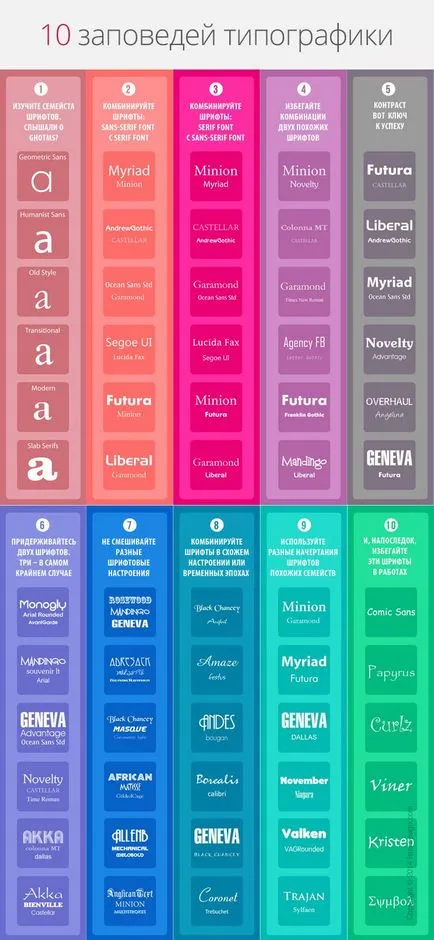
Как да изберем правилния шрифт за логото пълната информация logowiks
Повечето дизайнери са съгласни, че изборът на шрифта - това е един от най-важните неща при създаване на лого. Сега на разположение хиляди шрифтове и е трудно да избера най-подходящия. Но има начини да се опрости процеса на подбор. Например, след като осъзнаят, че шрифтът е личност и какво точно е това, можете да изберете шрифт, който ще даде желаното качество на вашия бизнес.
Кои шрифтове се използват добре познати компании
Нека да разгледаме най-известните фирмени лога шрифтове и се опитват да разбера как работят, какво причинява на сдружението, тъй като те са интегрирани в марка на компанията.
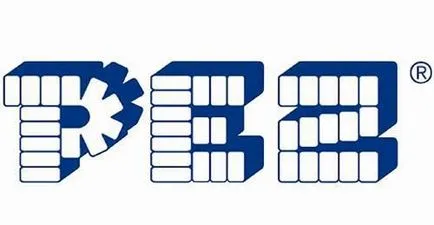
Pez бонбони производител използва шрифт, който е визуално представяне на един от видовете шоколадови бонбони. Font игрив, но просто, просто като играчка опаковка механизъм сладкиши.
Сценарият с процъфтява като Coca-Cola и Disney е свързано с нещо безплатно и приятелски, като логото си магическо.
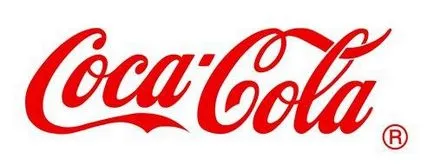
В същото време, вместо Citigroup избира малки букви шрифт без серифи, проектиране на изображението, което включва първи наличност.
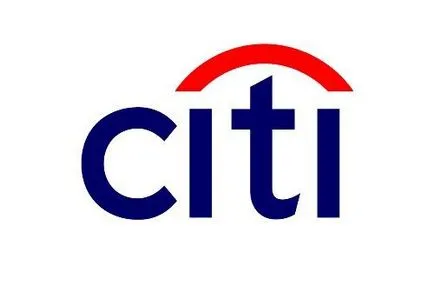
Всички основни шрифтове могат да се разделят на няколко типа: Serif (серифни), Сансерифни (без сериф), написана на ръка, Script, написани на пишеща машина, шрифтове с завъртулки Display.
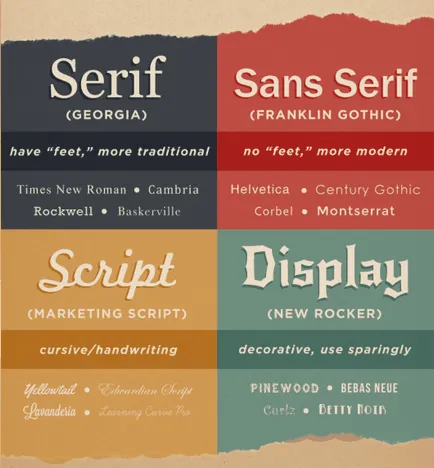
Сансерифни шрифтове изглеждат по-чисти и модерни, защото те не разполагат с линии в края на хода.
Script шрифтове изглеждат като текст, написани на ръка писалка, четка и т.н.
Script шрифтове изглеждат по-топли и привлекателни, но те са слабо разбираеми, така че те се използват само като главни букви в печатница.
Script шрифтове са много рафинирани и предполагат, лукс. Както и при скрипт шрифтове, те имат обща характеристика.
Fonts дисплея. обикновено резервен вариант за лого, защото те nestolko особен.
Пишеща машина Fonts имитатор на текста, въведен на пишеща машина.
Тези шрифтове са добре съчетани с шрифтове другите групи, за разлика от декоративни шрифтове.
Съвети за това как да изберете шрифт за лого
Преди да започнете да преглеждате шрифтовете изглеждат добре на уебсайта на фирмата или проект. Задайте си няколко въпроса:
- Каква е образ на моята фирма?
- Какви качества правят клиентите стойност?
- Какво бихте искали да подчертаем - надеждност, креативност, стабилност?
- Ако можехте да избирате три думи да се опише вашата марка, какви биха били те?
- Кой е вашият идеален клиент?
Това е важно, защото всеки шрифт вашето настроение и личност. Тя може да бъде сериозна, ежедневни, игриво или усъвършенства. Трябва да се определи това, което искам да предам с помощта на текст, както и дали то да отговаря на вашия дизайн.
Ако качеството, което предава на шрифта не съвпада с цялостния дизайн на публикацията си, тя ще създаде визуална дисонанс за зрителите или ползвателите на вашия проект, и не е нужно това. Важно е да се обърне внимание на психологията на шрифта. След шрифта, като цвят, той има психологическо въздействие върху човешкото възприятие.
Изберете шрифт, който не се основава на лични предпочитания
Имайте предвид, духа и характеристиките на Вашия бизнес
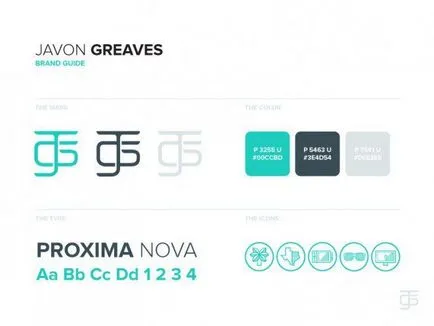
Не забравяйте, че с шрифт, който е най-перфектно въплъщава образа на вашата марка ще има огромно влияние върху съзнанието на клиентите си и да се превърне в култ, ако се прави правилно.
Не копирайте конкуренти
Вероятно, че винаги искат да са наясно какво правят вашите конкуренти. Не защото искате да копирате техния стил или открадне нещо, а защото искате да знаете какво правят, така че можете да се учат от грешките, вижте какво са направили правилно, и за да се избегне непреднамерено прилики. Най-малкото, че би било правилно да се направи. Поради това, очевидно не използват едни и същи шрифтове като конкурентите си.
Бъдете оригинални
Искаш ли да се направи всичко възможно, за да бъде оригинална, докато все още остава верен на посланието на вашата марка. Добра идея - купи шрифта за логото си на шрифта Store сайт, а не да се избере един от шрифтовете, които са инсталирани с текстообработваща програма или е в публичното пространство. Тези шрифтове се използват твърде често за други компании.
Изберете прости шрифтове
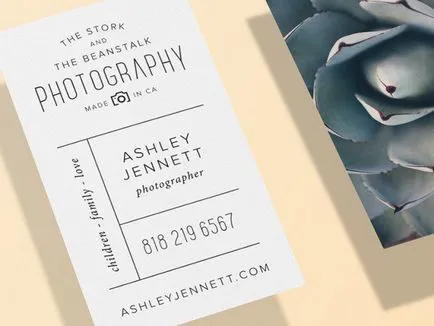
Как ще избрания шрифт в различни среди
Шрифтове ще варират в зависимост от размера, дали те ще бъдат отпечатани на хартия или да се използват в мрежата. Някои шрифтове могат да станат нечетливи или непривлекателни.
Избягвайте популярните шрифтове
Стой настрана от време
Запомни тези диско шрифтове от края на 70-, които приличаха на животни, балони? Те бяха на мода в продължение на няколко години, а след това изчезна. Не забравяйте, че вашето лого трябва да застане на капризите на дизайна, и това се отнася за вашия шрифт.
Ако всичко изведнъж се използва специфичен шрифт (като повсеместното Скица блок), опитайте нещо друго. В края на краищата, вие искате да направите логото си се открояват и въпреки, че изборът на тенденция на шрифта изглежда просто решение, ще съжалявате година по-късно.
Богата колекция от най-различни шрифтове от Google. Всички от тях са безплатни и могат да бъдат изтеглени на компютър за използване в различни приложения или да се свърже с вашия сайт.
Развитието на известния лога